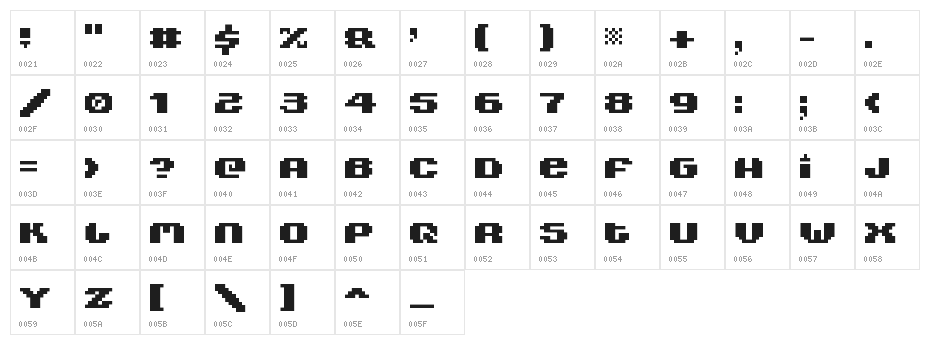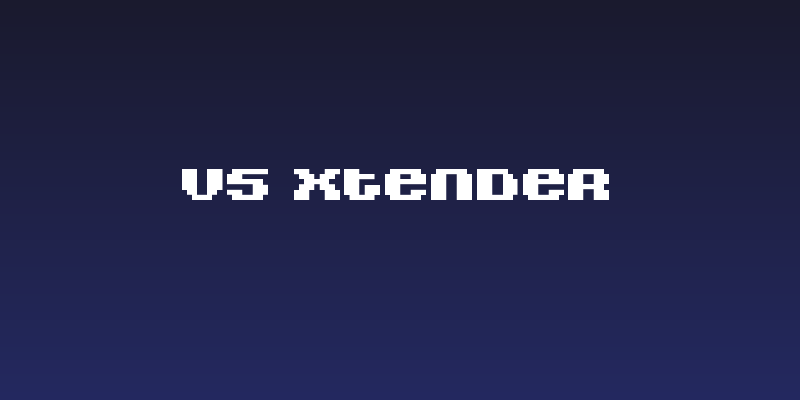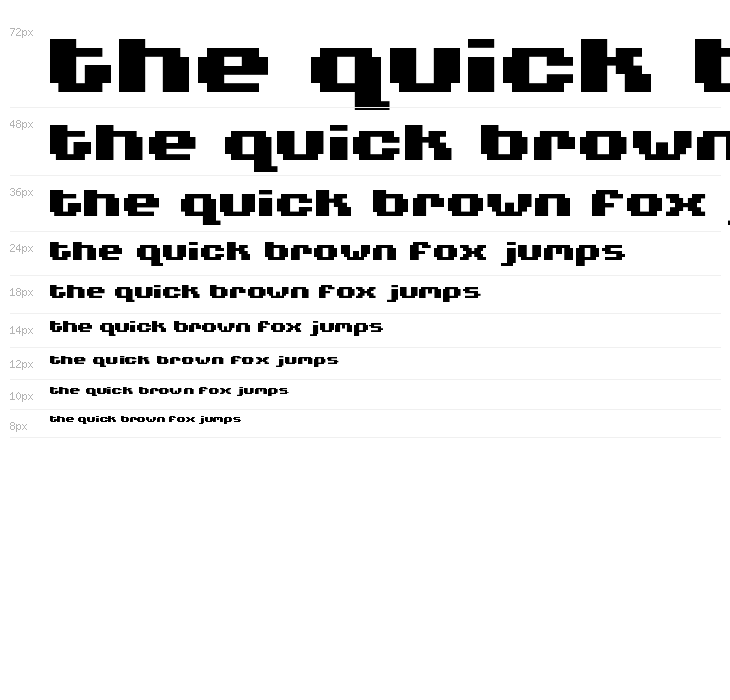
V5 Xtender Font
| Categorie | Pixel |
| Stile generale | Retro, Digital |
| Progetti proposti | Ideal for video game graphics, tech branding, retro-themed posters, and digital art projects. |